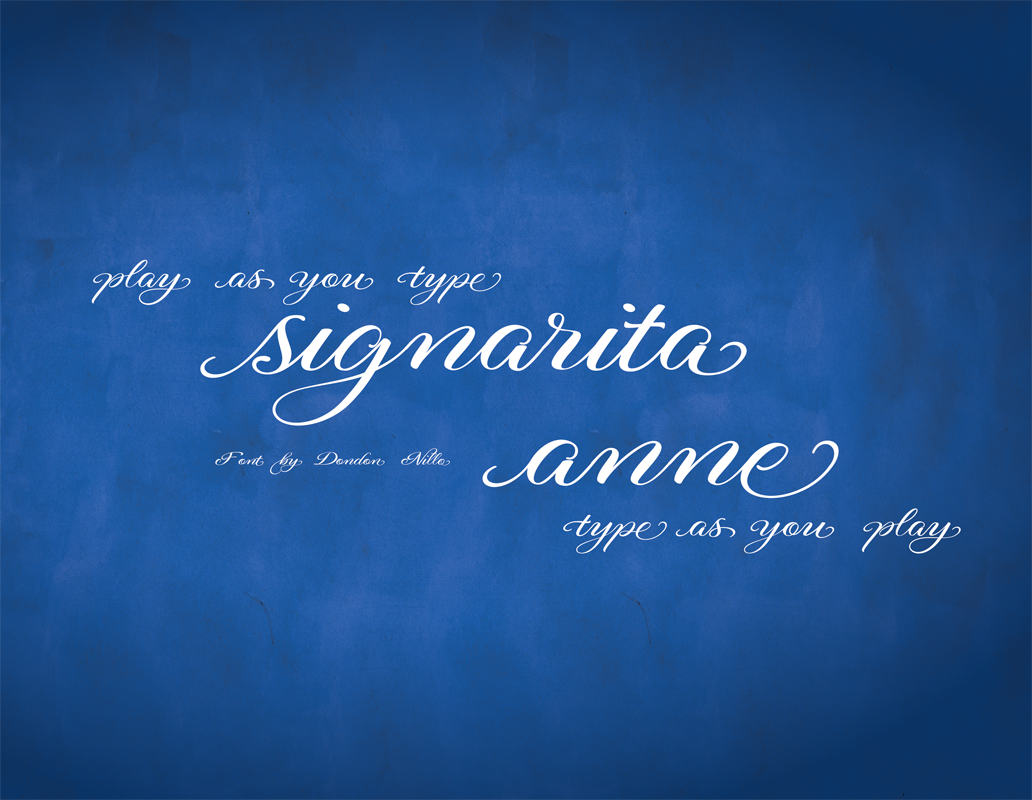
A fonte “Signarita Anne” é perfeita para artistas de arte livre que desejam adicionar um toque elegante à sua obra. Desenvolvida pelo designer Hamilton, esta fonte tem um charme natural e delicado, especialmente adequada para aplicativos de escrita artesanal ou criação de anotações pessoais. Com linhas suaves e formas arredondadas, a “Signarita Anne” oferece uma opção versátil para escritas manuscritas. Suas características incluem um estilo elegante que se assemelha ao desenho de mão delicada, sem perder seu caráter moderno e versátil. Este design é perfeito para aplicativos de arte livre como letras folheto ou anotações pessoais, onde você pode expressar sua personalidade através da escrita. A fonte “Signarita Anne” é uma excelente opção para quem busca dar um toque de sofisticação à sua obra. Seja você um designer gráfico profissional ou um entusiasta do design de arte livre, a font “Signarita Anne” é certamente o item para adicionar ao seu arsenal. Seu estilo único e suave certamente vai destacar em qualquer projeto que você escolha apresentar.